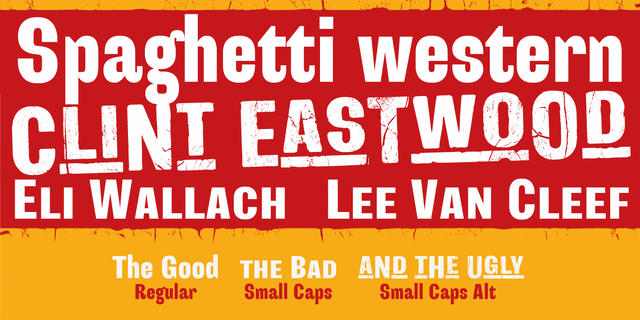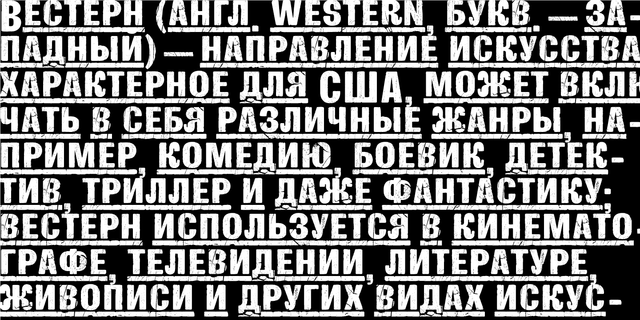
GoodBadUgly – это гротеск в духе Дикого Запада. Это семейство шрифтов будет отличным решением для журнальных заголовков, плакатов, вывесок, упаковки, логотипов. Шрифт разработал Кирилл Ткачев в 2013 году.
Ассоциации c начертанием GoodBadUgly RegularКачества и характер:
важный, громкий, мотивирующий, амбициозный, ровный, статичный, заметный, ироничный, солидный, старомодный, устойчивый, стабильный, тяжелый, убедительный, авторитетный, твердый, качественный, ремесленный, трудолюбивый, надежный, консервативный, бытовой, гангстерский, блатной, крафтовый, винтажный, грубый, броский, добротный, крепкий, деревянный, ностальгический, рабочий, резкий, четкий, брутальный, кондовый, оригинальный, характерный, сильный, тесный, мужественный, мачо, ковбойский, яркий, активный, жесткий, суровый, самобытный, странный, интересный, причудливый, бандитский
мафия, карты, торговля, продукты, запас, склад, консервы, посылка, груз, ящик, ремесло, кузнец, мясо, ремонт, ужин, гамбургер, казино, плотник, древесина, ярмарка, закуска, еда, лавка, фермер, шахта, шахтер, вагон, джинсы, обувь, салун, ковбой, ранчо, трактир, кино, револьвер, виски, обед, игра, техника, инструмент, машина, железная дорога, паровоз Стилистика: